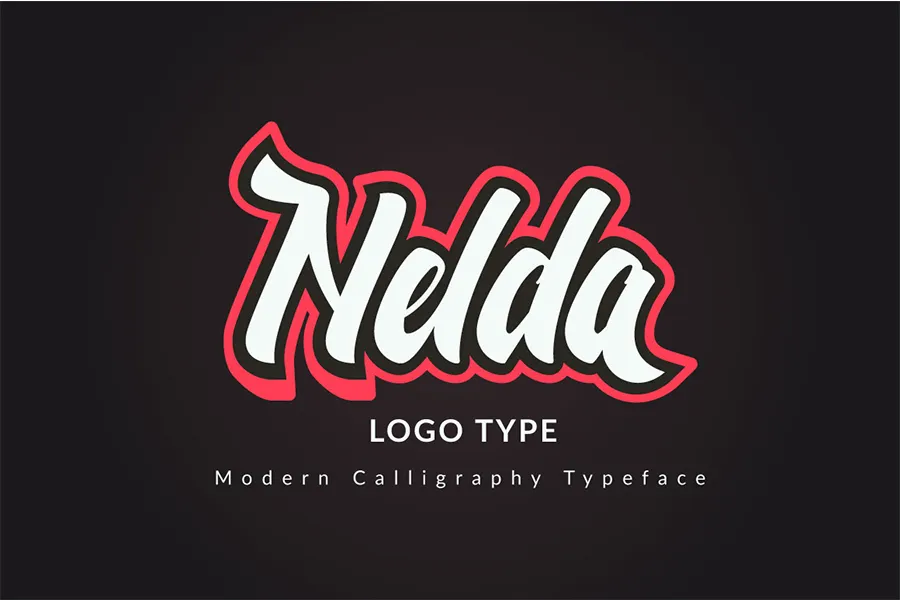
Nelda Typeface – Download Grátis
A Nelda Typeface é uma fonte playfull que se destaca entre as demais por sua fusão única entre letra cursiva com traços ásperos e a escrita manuscrita natural. Esta fonte moderna, versátil e bold combina elementos de letra aquarelada e textura da escrita à mão para criar um resultado impressionante. Perfeita tanto para logos como para embalagens, headlines e posters, a Nelda também é uma excelente escolha para adicionar o toque personalizado aos tênis ou qualquer outro tipo de artefato que precise de um texto inconfundível. É perfeitamente adaptada para diversas aplicações, garantindo que sua marca ou produto possa se destacar com uma fonte atraente e única. Esta fonte foi projetada pelo designer Hamilton e oferece uma maneira divertida e criativa de incorporar personalidade em qualquer projeto.